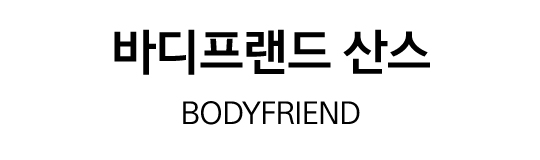
일정한 자폭과 여유 있는 골격이 명료하고 활기찬 인상을 주며, UI에 최적화된 3가지 굵기로 다양하게 사용할 수 있습니다.
| 프로젝트명 | 바디프랜드 UI 전용서체 'Bodyfriend Sans' |
| 스펙 |
한글 2,350자 / 영문 94자 / 약물 986자 / 프랑스어, 이탈리아어 / 리가처 7자 / 추가 심볼 2자 |